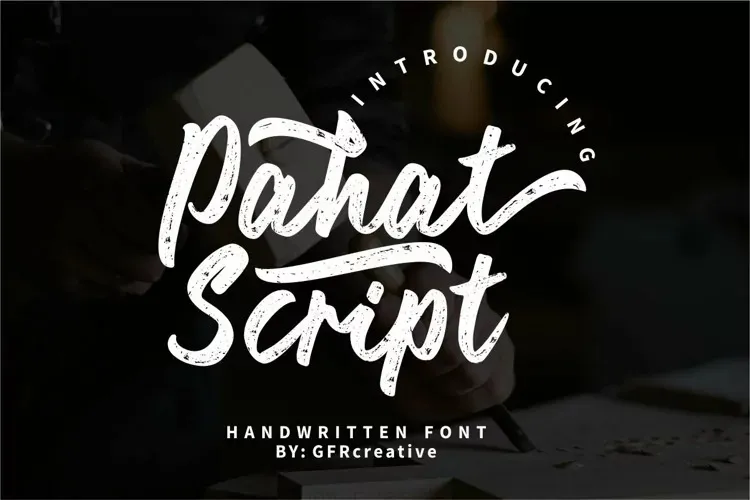
Pahat Script Font – Download Grátis
A fonte ‘Pahat Script Font’ é uma obra-prima para aqueles que desejam adicionar personalidade e sofisticação a seus projetos digitais. Criada por mãos dedicadas de artistas, esta fonte serifada tem o poder de dar vida à sua ideia, transformando-a em arte natural e autêntica. Com um toque suave do mouse ou das canetas digitais, você pode aplicar uma capa única e inovadora às suas criações, seja para trabalhos de identidade visual, design gráfico, arte digital, até mesmo para projetos como cartões de convite, embalagens de produtos, selos de eventos especiais. ‘Pahat Script Font’ é perfeita para aqueles que buscam um toque especial em seus materiais digitais, seja através dos pequenos detalhes ou da forma como toda a composição se funde na criação final. Este é o tipo de fonte com o qual você pode transformar qualquer projeto em uma peça única e memorável.